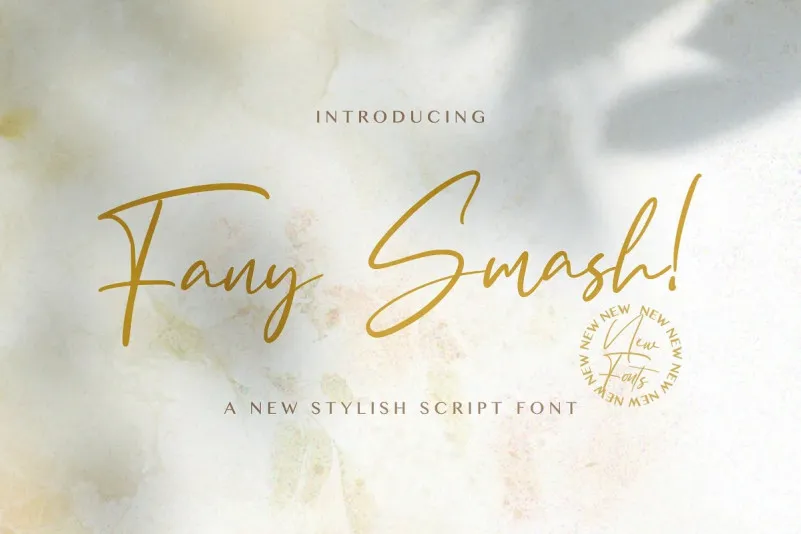
Fany Smash Font – Fonte Grátis
Fany Smash Font
A Fany Smash Font é uma elegante fuente escrita à mão que captura a essência do estilo script moderno. Desenvolvida pelo StringLabs, essa fonte possui linhas fluidas e tipografia cuidadosamente equilibrada, resultando em caracteres bonitos e bem balanceados. Suas características são tão versáteis quanto o seu design, tornando-a uma escolha ideal para designers buscando adicionar um toque de criatividade a seus projetos. Seja para criações gráficas inovadoras ou até mesmo pequenos elementos, essa fonte tem o potencial de transformar suas ideias mais imaginativas em algo realmente vívidos e impactantes. Adicionar Fany Smash à sua próxima criação é uma ótima maneira de destacá-la com estilo e elegância.